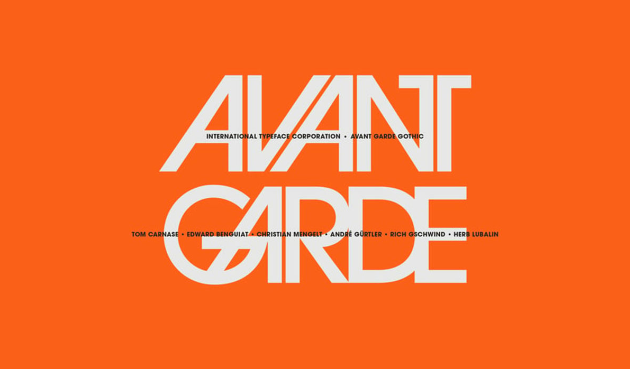
Tác giả: Herb Lubalin và Tom Carnase
Ngày phát hành: 1970
Bộ Font: Avant Garde Family
Phân loại: Sans-serif
Kiểu chữ: Geometric
Độ dày: Light, Book, Medium, Bold, Extra Bold
Font Avant Garde là một kiểu chữ thuộc bộ font chữ không chân mang tính biểu tượng, được thiết kế bởi Herb Lubalin và Tom Carnase vào cuối những năm 1960. Với các đường nét hình học và cân đối, font Avant Garde nổi bật với sự hiện đại và tiên phong trong thiết kế. Đặc trưng bởi các ký tự có dạng hình tròn và chữ in hoa dễ nhận biết, font này thường được sử dụng trong logo, tiêu đề, và tài liệu quảng cáo để truyền tải thông điệp mang tính đột phá và sáng tạo. Font Avant Garde thuộc phân loại sans-serif, nổi bật với thiết kế đơn giản, không chân và dễ đọc.